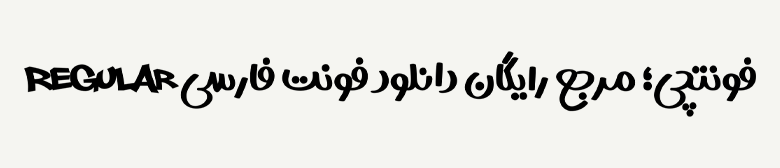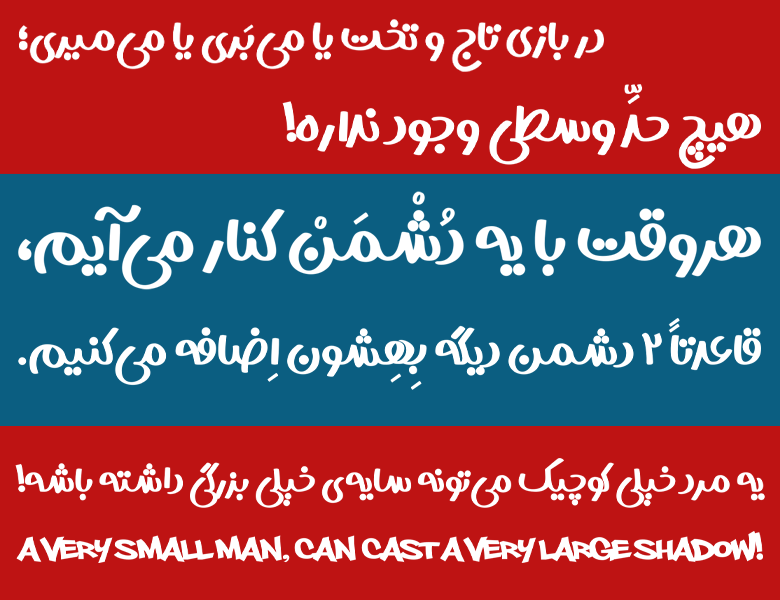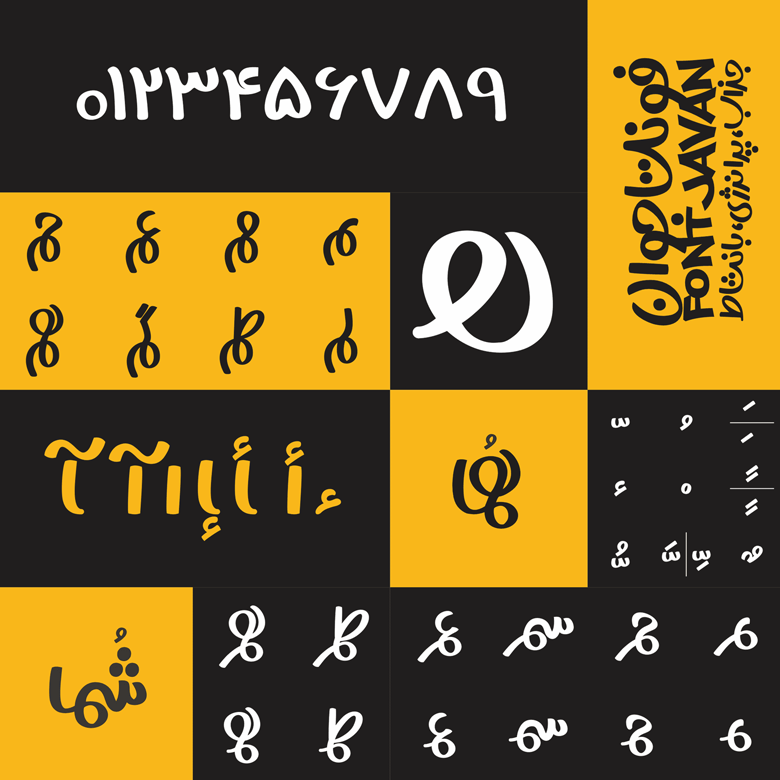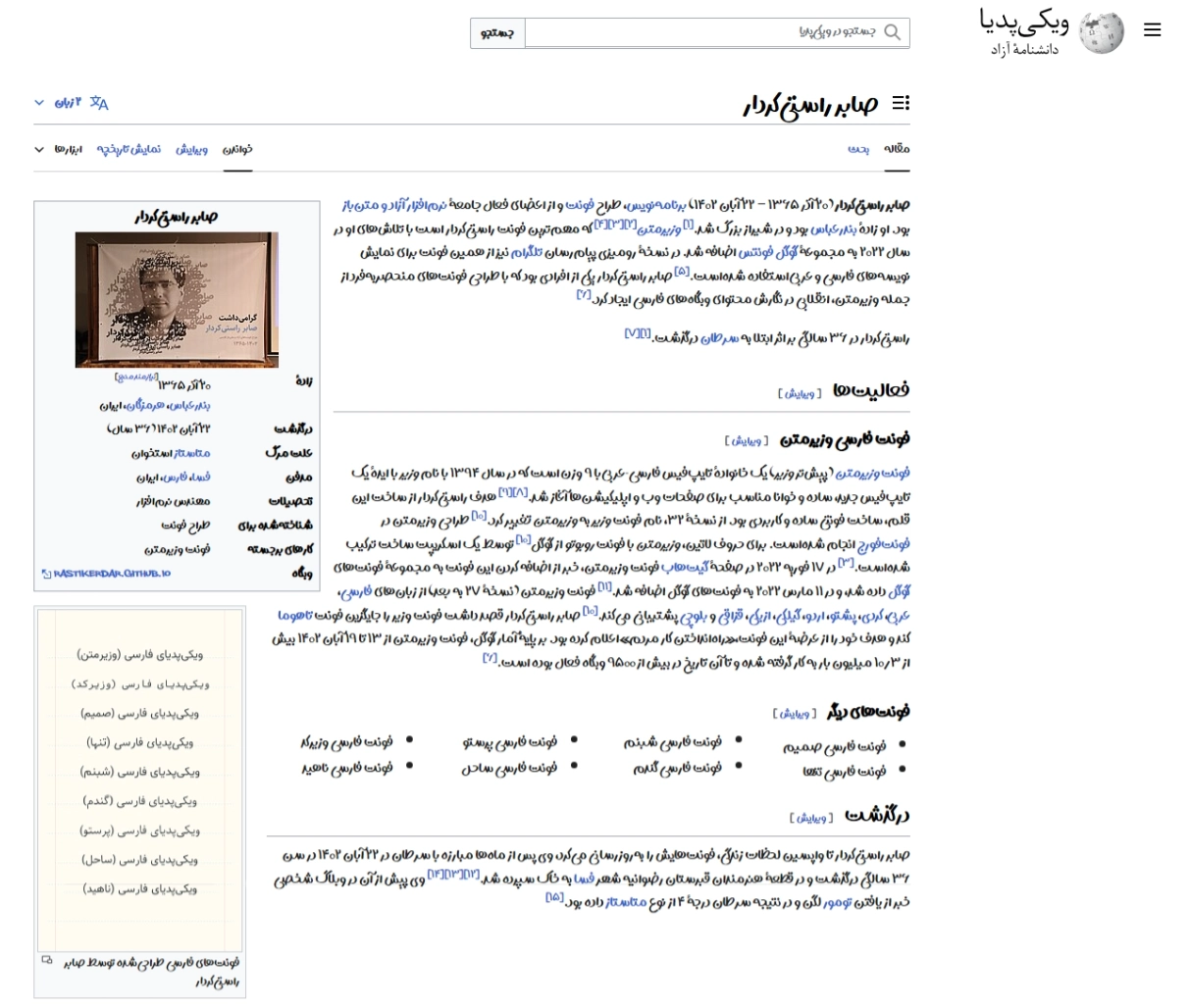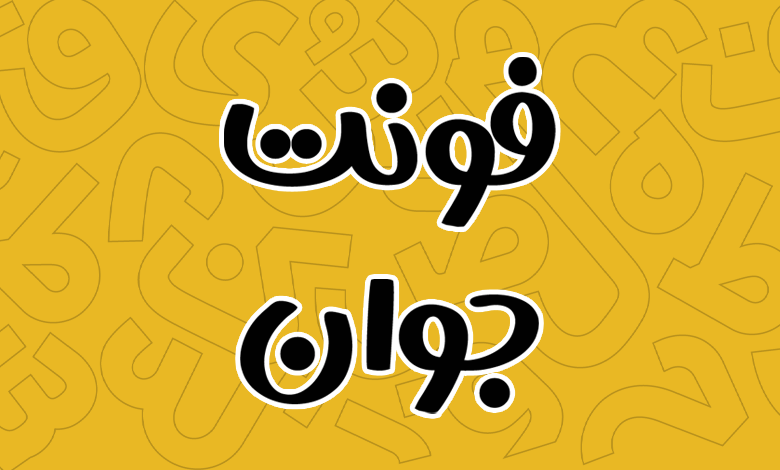
فونت جوان (Javan)
فونت جوان (به انگلیسی: Javan) از سری فونتهای نمایشی و دستنویس مناسب برای عناوین، تبلیغات و استفاده برای کتابهای مصور کودک و نوجوان است که توسط قاسم نجاری طراحی و ساخته شده است. این فونت دارای طراحی کاملا با نشاطی است که سرشار از خمیدگی، دایرهها، چشمیهای ناهمگون و تحرکات بسیار است. فونت جوان رایگان نیست و در یک بسته شامل وزن معمولی قابل خریداری است.
در طراحی فونت Javan از قلم ماژیکی استفاده شده است و حروف و ترکیبات طوری در کنار هم قرار میگیرند که گویی با استفاده از ماژیک غرق بر روی کیبورد خود باشید. ایده اصلی شکلگیری این فونت نیز از آثار گرافیکی و امضاهای متعدد گرافیتی الهام گرفته شده است که بهوفور در دنیای امروز یافت میشوند.
فونت جوان با گرد هم آوردن این ترکیبات و آثار کار را سادهتر کرده است که به سادگی میتوانید بر اساس سبک آثار ماژیکی به طراحی هر چیزی بپردازید. در ادامه این نوشته از وبسایت فونتچی به نقد و بررسی قلم جوان خواهیم پرداخت؛ قلمی که با داشتن یک وزن ثابت، در عینحال که پویایی و کنتراست به شدت بالایی دارد، به ما در طراحی هر چیزی کمک خواهد کرد.
معرفی و بررسی فونت جوان (Javan)
مسلما شما هم با اولین نگاهی که به فونت جوان داشته باشید، ناخودآگاه یاد دوران کودکی و ساخت کارهای گروهی روزنامه دیواری در دهههای ۶۰ و ۷۰ خواهید افتاد. در آن روزگاران در هر مدرسهای میشد انواع روزنامه دیواری را یافت که در سالن اجتماعات هر مدرسهای بر روی تابلو اعلانات خودنمایی میکرد.
یکی از بهترین کاربردهای فونت جوان نیز همین مورد است. میتوانید از این فونت برای طراحی انواع مطبوعات استفاده کنید؛ در کارهای تبلیغات خلاقانهای که خصوصا در حوزه کودک و نوجوان است از آن بهره ببرید یا اینکه از آن برای ساخت کتابهای مصور و اپلیکیشنهای آنلاین برای انتقال حس بهتر از محتوا استفاده کنید.
وزن و سبک فونت جوان
با اینکه وزن فونت معمولی است، اما از ضخامت و پهنای خاصی برخوردار است که در شکستگی، خمیدگیها و چشمی حروف دارای ضخامتی کم است که همان حس جوانی «دل به دریا زدن، ریسک کردن و خطر پذیری» را منتقل میکند. در بخشهای دیگر همچون نقاط و بخشهایی از حروف که ماژیک در حال عمود شدن است نیز پهنای چشمگیری دارد که به زیبایی و داشتن کنتراست بیشتر این فونت کمک میکند.
عنوان و نمایشی بودن این فونت آن را به گزینهای برای استفاده در موارد متعددی تبدیل کرده که یکی از پرطرفدارترین آنها، بسته بندی محصولات غذایی است. سایر موارد کاربرد این فونت را هم با توجه به امکاناتی که دارد در بخشهای دیگر فونت معرفی خواهیم کرد که پیش از دانلود فونت جوان بد نیست نگاهی به آنها داشته باشید.
این مدل طراحی فونت را در انواع فونت دست نویس میبینیم. فونتهایی که کاملا حس شادابی دارند و ضمن داشتن سبک متفاوت در طراحی حروف و نقاط که شاید اصلا حتی مکمل یکدیگر نبوده و کاملا ضد هم بهنظر برسند، اما در نتیجه کلی زیبایی چند برابری به فونت خواهند داد.
پشتیبانی از زبان عربی و انگلیسی
فونت جوان فارسی محدود به این زبان شیرین نیست و از زبانهای عربی و انگلیسی نیز پشتیبانی میکند. در نسخه لاتین این فونت خبری از فونت دیگر یا استفاده از یک فونت دستنویس انگلیسی با لایسنس رایگان نیست و سبک و استایل فونت کاملا مطابق با حروف فارسی برای زبان انگلیسی ساخته شده است.
همان حس جوانی، تحرک، ظرافت و پویایی در نسخه انگلیسی هم رعایت شده و حروف با ظاهری که گاها در همتنیده و چسبان هستند تا یکدیگر را حمایت کنند، در برخی ترکیبات از یکدیگر فاصله دارند. شاید فکر کنید که این مسئله مشکلی است که در فونت وجود دارد؛ در حالی که استایل فونت در زبان لاتین بههمین شیوه پیادهسازی شده تا حس و پویایی نشاط جوانی بهتری را القا کند.
در فونت عربی جوان تغییرات خاصی نمیبینیم و هرآنچه در نسخه فارسی وجود دارد برای زبان عربی نیز قابل استفاده است. تنها نکتهای که باید به آن اشاره کرد، پشتیبانی کامل از اعراب و همچنین ظاهر خاص برخی کلمات است که آن هم از تنوع بسیار بالایی که این فونت در حروف و ترکیبات جایگزین دارد نشات میگیرد که در ادامه به بررسی آنها خواهیم پرداخت.
دارای ترکیبات و حروف جایگزین بسیار متنوع
ویژگی اصلی و مهم فونت جوان پشتیبانی از حروف جایگزین و ترکیبات خاص است که نسبت به سایر فونتها آن را در یک سطح دیگری قرار داده است. با اینکه اکثر فونتها این ترکیبات را شاید به تعداد محدودتر نزدیک به انگشتان دو دست داشته باشند، در این فونت با تنوع بسیار بالاتری مواجه هستیم.
حروف جایگزین در بیشتر حروف فونت جوان از جمله «الف، ب، پ، ت، ث، س، ش، ص، ض، ع، غ، ف، ق، ک، گ، م، ن، ه، ی» وجود دارد.
جدا از این برخی ترکیبات مثل «ـم، ـر، سـ، شـ» که در ابتدا و انتهای کلمات یافت میشوند، نیز امکان استفاده از چند سبک مختلف را در اختیار شما قرار خواهند داد.
در نتیجه: فونت جوان برای استفاده در کارهای گرافیکی که نیازمند سبک ماژیک برای پیادهسازی هستید به شما کمک خواهد کرد. حتی میتوانید از این فونت با ترکیبی در کنار سایر فونتها استفاده کرده و از آن برای طراحی لوگو تایپ یا وردمارکهای خود استفاده کنید.